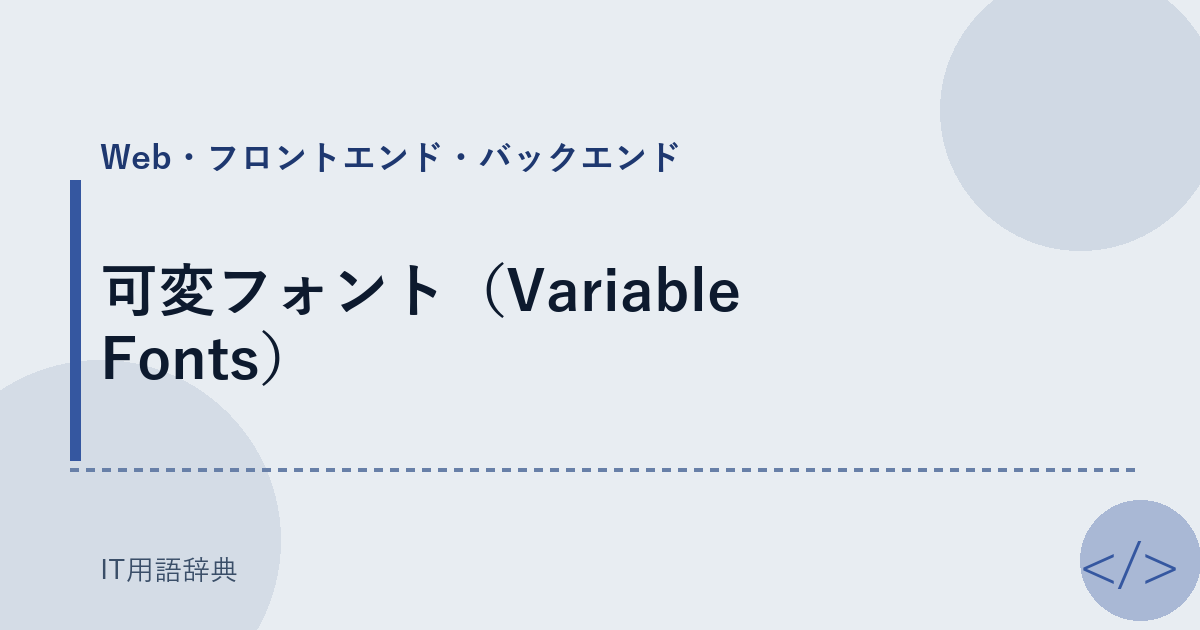
可変フォントとは、一つのファイル内で異なる書体スタイルを表現できる最新技術です。2016年にGoogle Fontsが開発し、その後W3Cによって標準化されました。この記事では、その背景と機能的側面について詳しく紹介します。
可変フォントの概要
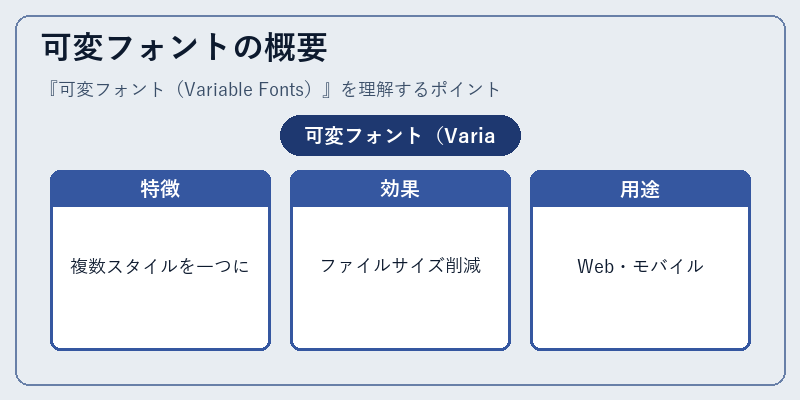
可変フォントは、さまざまなデザイン要素を持つ一つのテキストフォーマットとして注目を集めています。具体的には、ウェブサイトやアプリケーションでの利用に適しています。しかし、この技術が果たす役割はそれだけにとどまりません。
例えば、ウェブページ上の特定の部分では強調表示のために太字を使用し、別の部分では読みやすさを優先する細字を使用したいと考えるデザイナーも多いです。これにより一貫性を持った視覚的な表現が可能となるのです。
可変フォントの構造
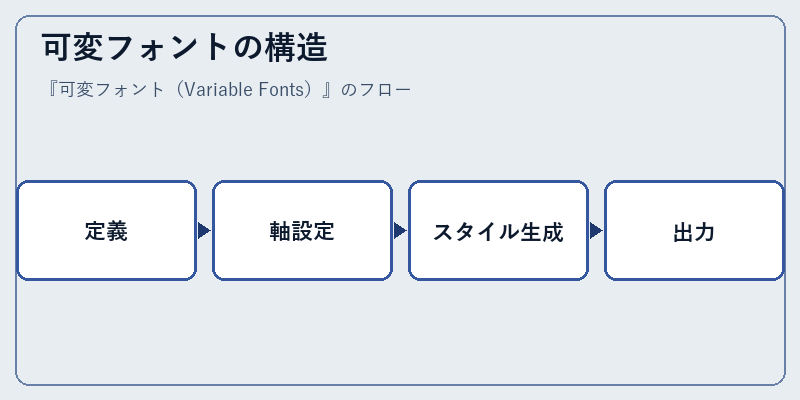
可変フォントには特別なファイル形式が採用されており、その設計は複雑さを内包しています。まず最初に、各書体の主要な特性を特定します。これは通常、ウェイトや幅といった要素に基づいて行われます。
次に軸(axes)と呼ばれるコンポーネントを設定し、それらが動的に変化する様式を定義します。これにより、ユーザーは特定の軸値を指定することで、その間にあるあらゆる書体スタイルを得ることができます。
可変フォントの活用例
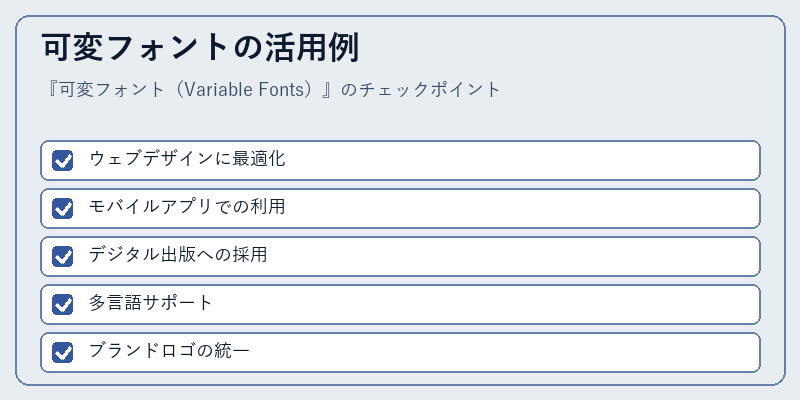
可変フォントは、現代的なウェブサイトやアプリケーションで広く使用されています。その柔軟性と効率性により、開発者はより洗練された視覚的体験を提供することができます。
また、多言語環境においても、可変フォントの利点が活かされます。異なる文字セット間でのスムーズな切り替えや互換性向上といった恩恵があります。
まとめ
可変フォントは、現代のWebデザインとフロントエンド開発にとって不可欠な要素となっています。その進化と共に、ウェブ上における表現力と効率が更なる向上を遂げていくことでしょう。